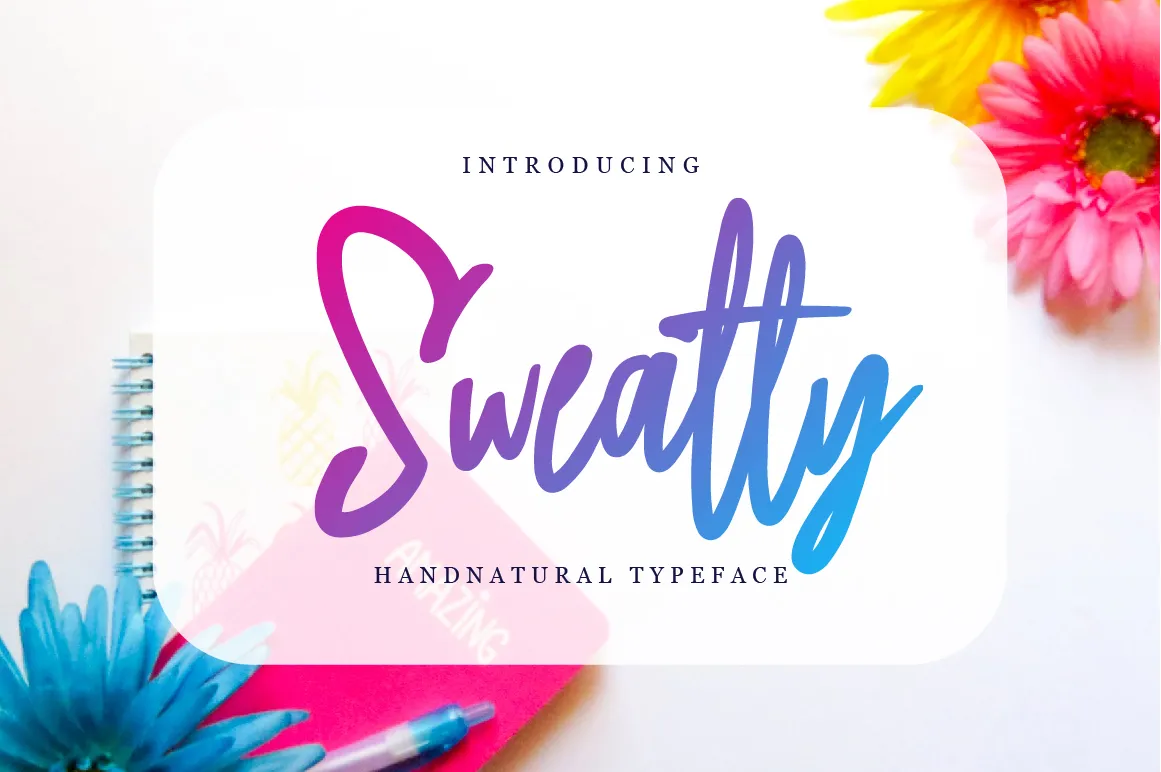
Sweatty Handwritten Natural Font – Download Grátis
Esta fonte é perfeita para designers profissionais que buscam uma escrita entrelaçada e natural para seus projetos digitais. Suas características elegantes e fluidas permitem que você personalize sua identidade visual de forma única, seja criando um logotipo brilhante ou decorando cartões de convite com estilo. Através do studioaktype, podemos garantir que esta fonte será perfeita para qualquer necessidade de design. Seja em uma impressão tradicional ou em tecnologias mais avançadas como embossing ou bordados, a ‘Sweatty Handwritten Natural Font’ se adapta e brilha em todas elas. Através dela, você pode estabelecer sua marca com uma escrita autêntica que transmitirá confiabilidade e individualidade. A fonte é especialmente indicada para criação de identidades digitais e para designs de marcas mais elaborados onde se espera um resultado elegante e natural.